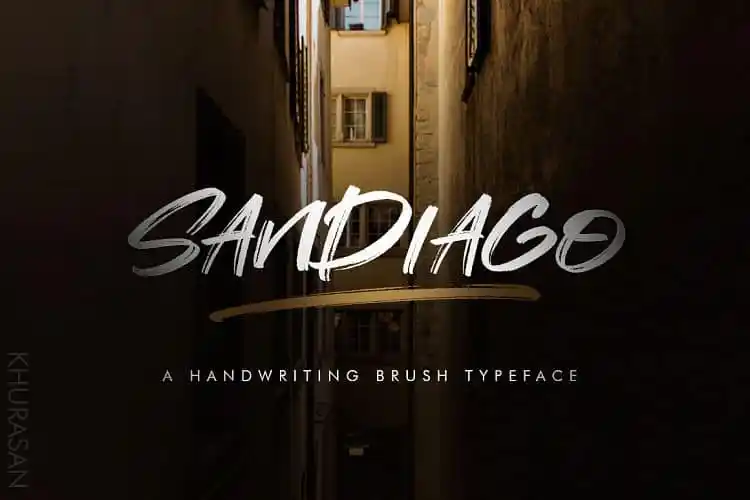
Sandiago Brush Font – Download Grátis
Introduzo-vos a uma nova fonte brush script chamada Sandiago Font. Desenvolvida por zziplex, esta é uma fonte livre e elegante que transmite um charme vintage sem ser exagerado. Intuitivamente escrita de forma casual e rápida, cada letra é criada com o auxílio das ferramentas de esfumar na superfície de papel. Sandiago abrange todo o alfabeto maiusculo, suportando várias línguas, dígitos, pontuação e também swashes. Ideal para múltiplos projetos criativos como logotipos, citações impressas, convites, cartões personalizados, embalagens de produtos, cabeçalhos, carta de encargo, fita de adesivo ou mesmo design para roupas, Sandiago Font é uma escolha perfeita. Esta fonte é especialmente útil para quem procura um charme vintage em suas criações digitais, oferecendo flexibilidade e personalidade para diversos tipos de projetos visuais.